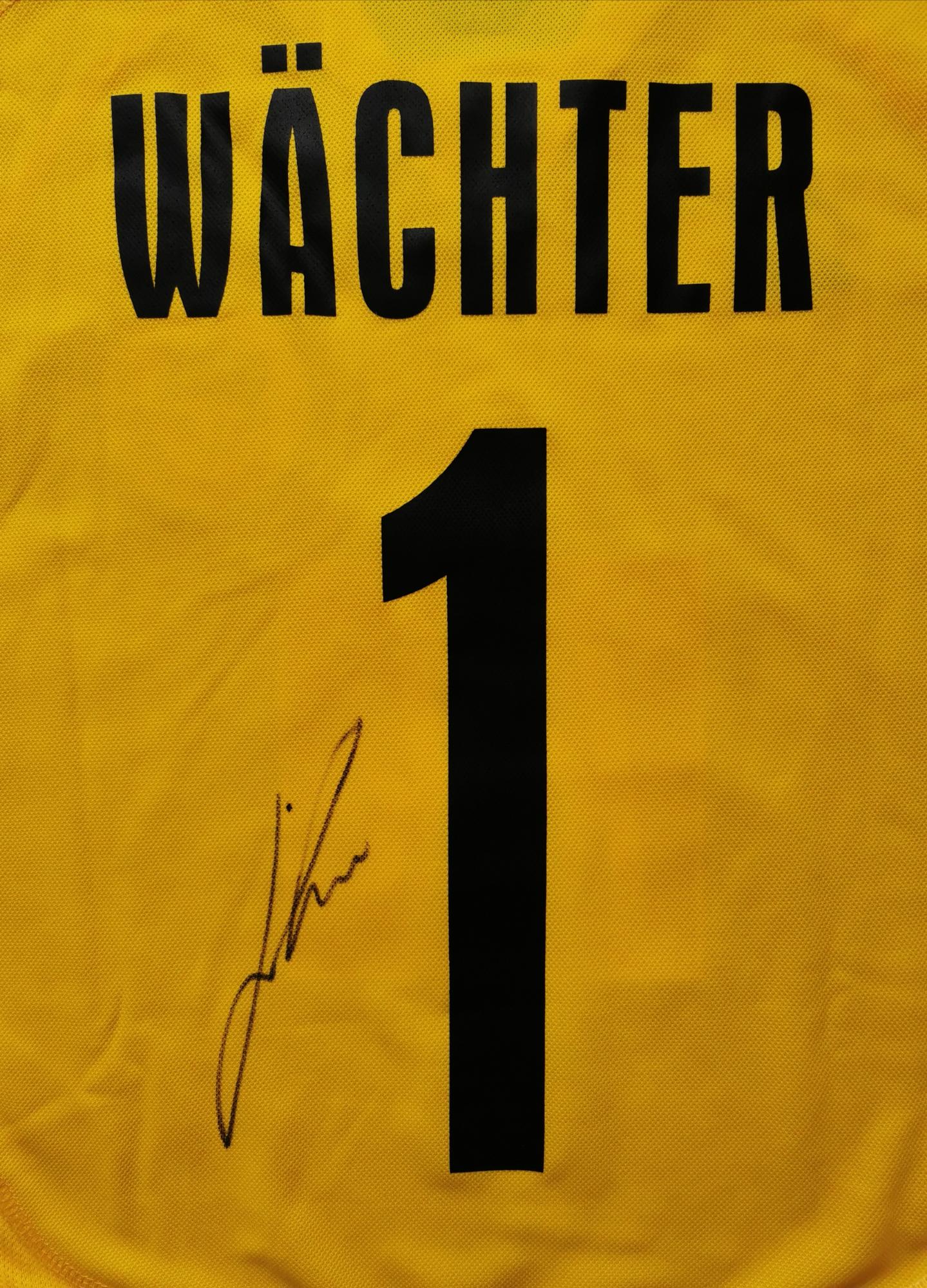
Suche Schrift von einem Fußballtrikot aus der Saison 2007/2008 (Hansa Rostock)
Ich suche die Schriftart der Hansa Rostock Trikots aus den Jahren 2006 bis 2008. Der Font darf auch was kosten.
Da passt die 2 leider auch nicht ganz.
Nachtrag: Du hast ja die "Aurora Condensed" verlinkt, nicht die Grotesk, da passt dann auch die 2.
welcher der großen Sportbekleider war denn in dieser Saison der Ausstatter von Hansa Rostock?  Gerade Trikot Schriften sind oft Hausschriften der Sportkleidungs Hersteller für jeeils diese Saison. Einfach um die Trikot-Fälscher etas von ihrem Tun abzuhalten. Die jeweilige Schrift ird dann oft auch markenrechtlich geschützt und nicht als Font veröffentlicht.